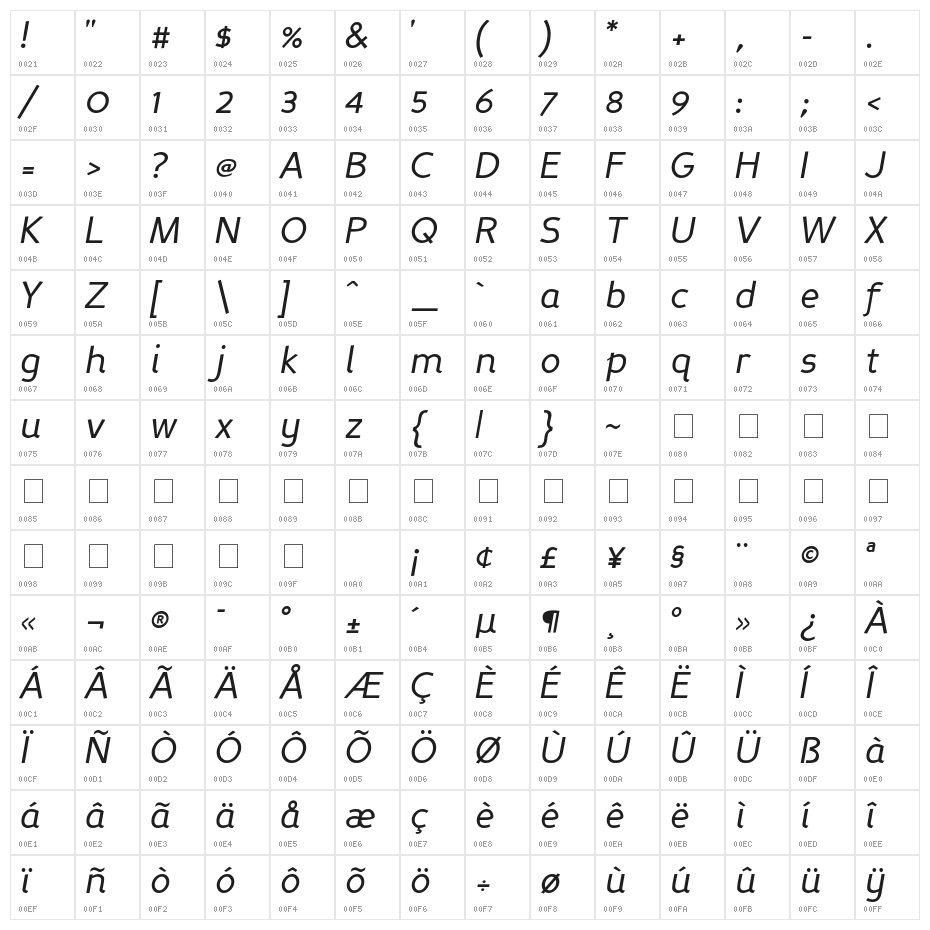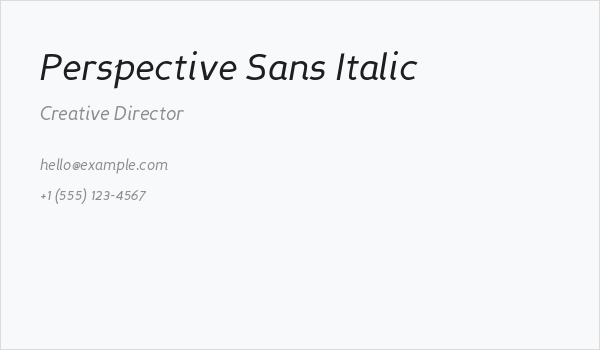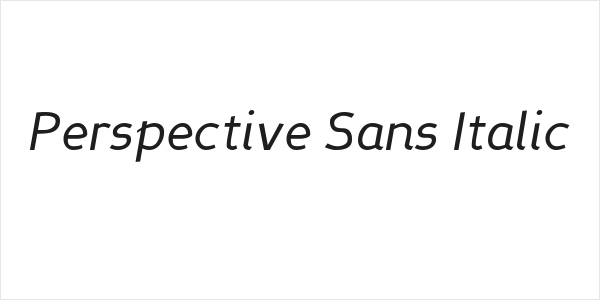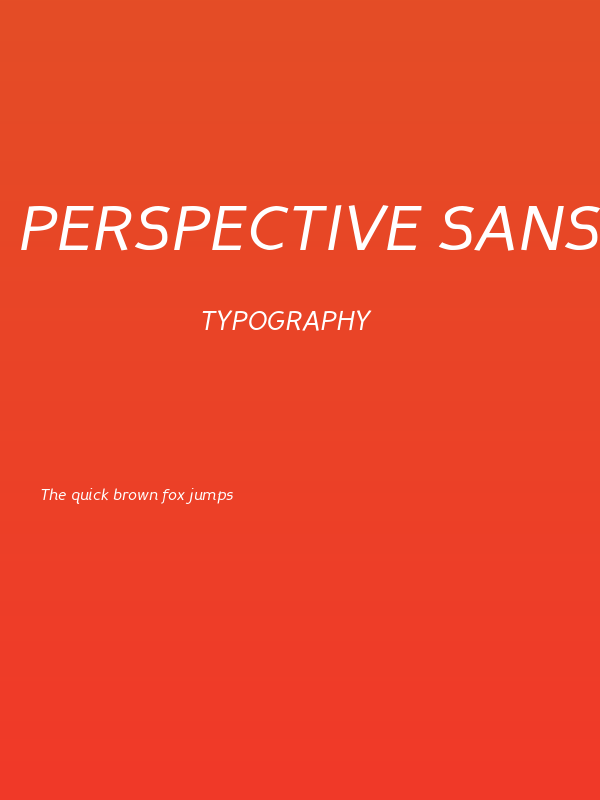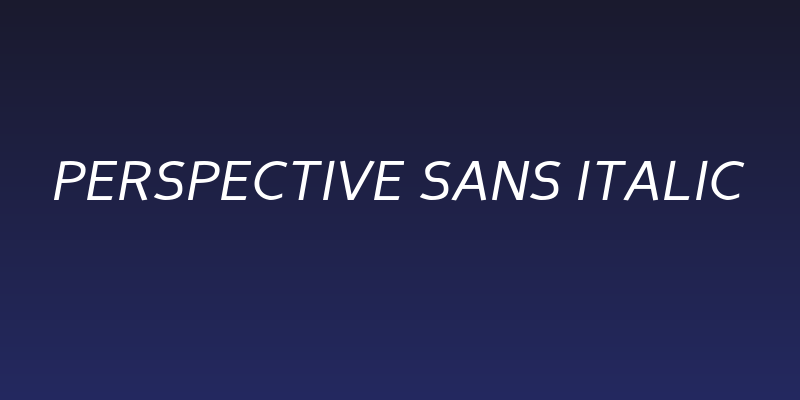
Perspective Sans Italic Font
| Progetti proposti | Ideal for branding, advertising, and editorial design projects where a modern and dynamic feel is desired. |